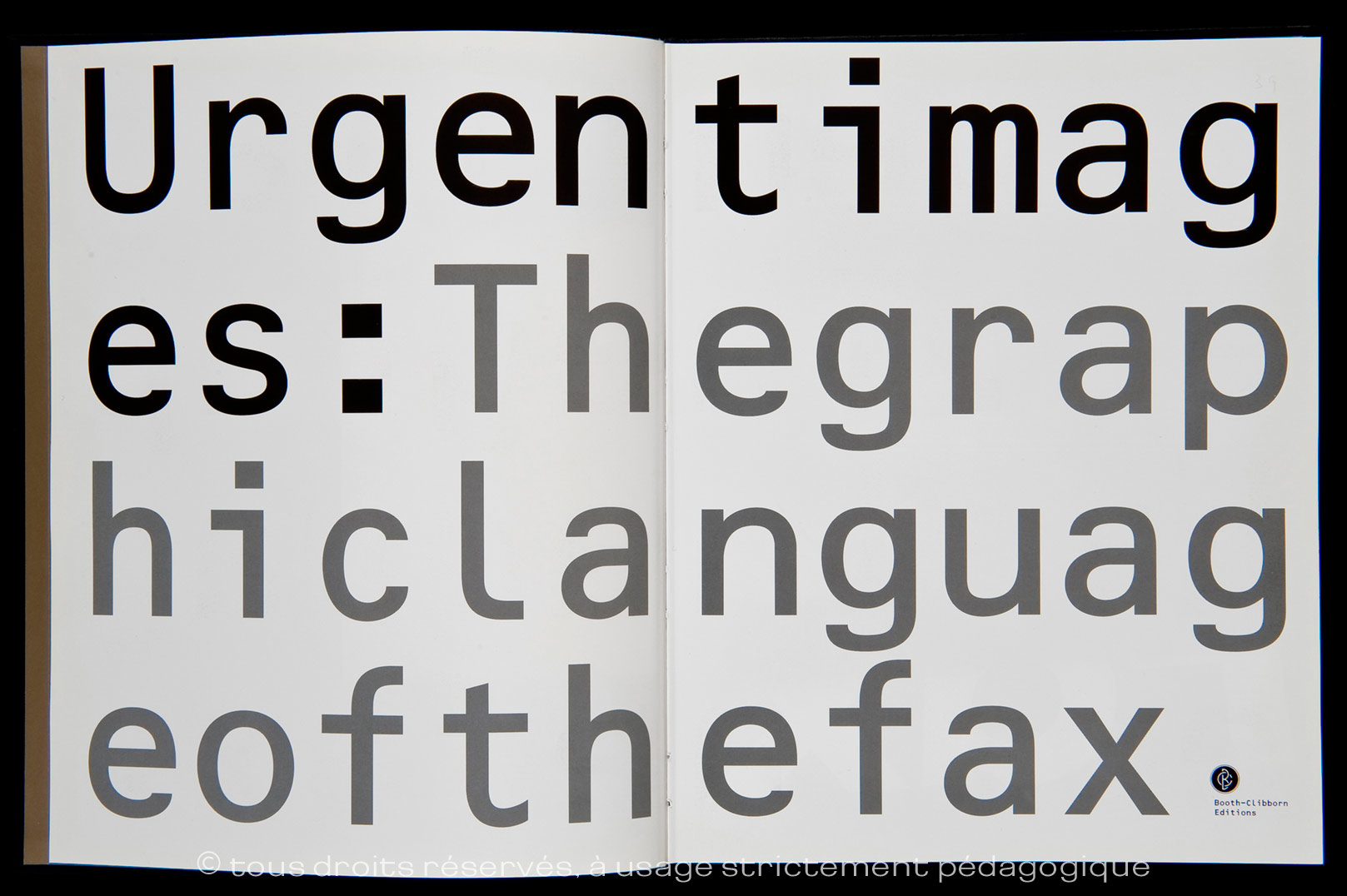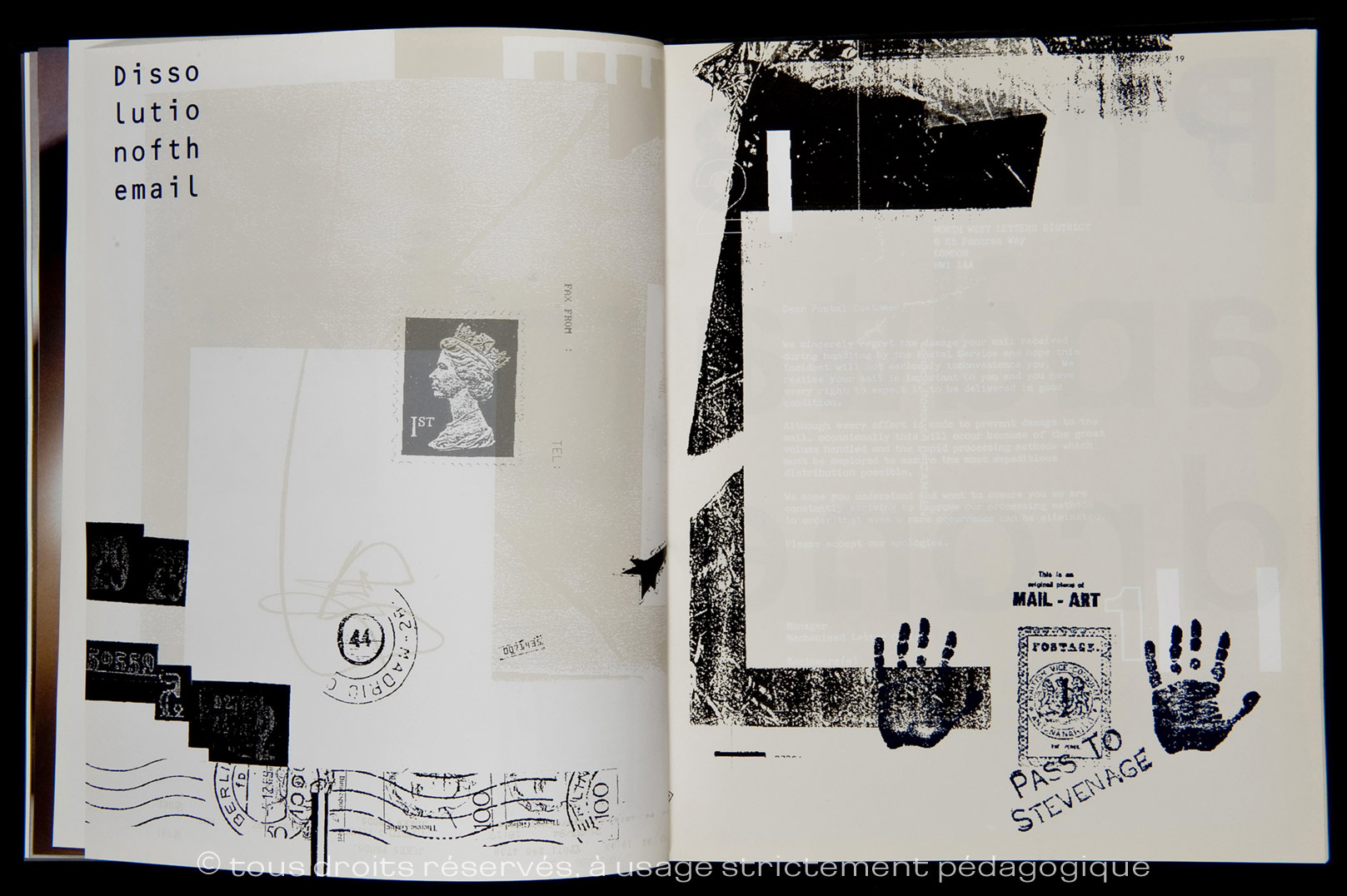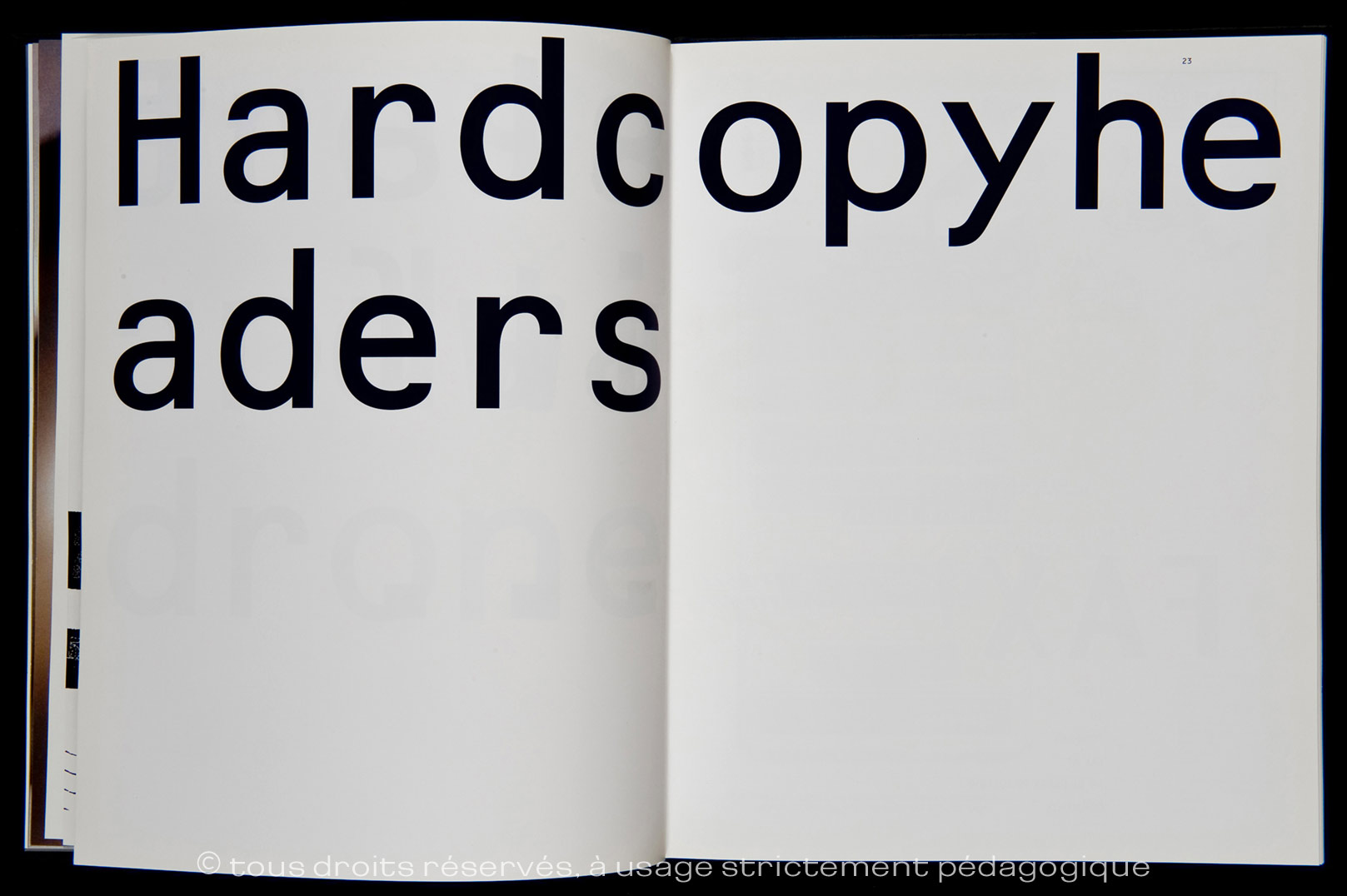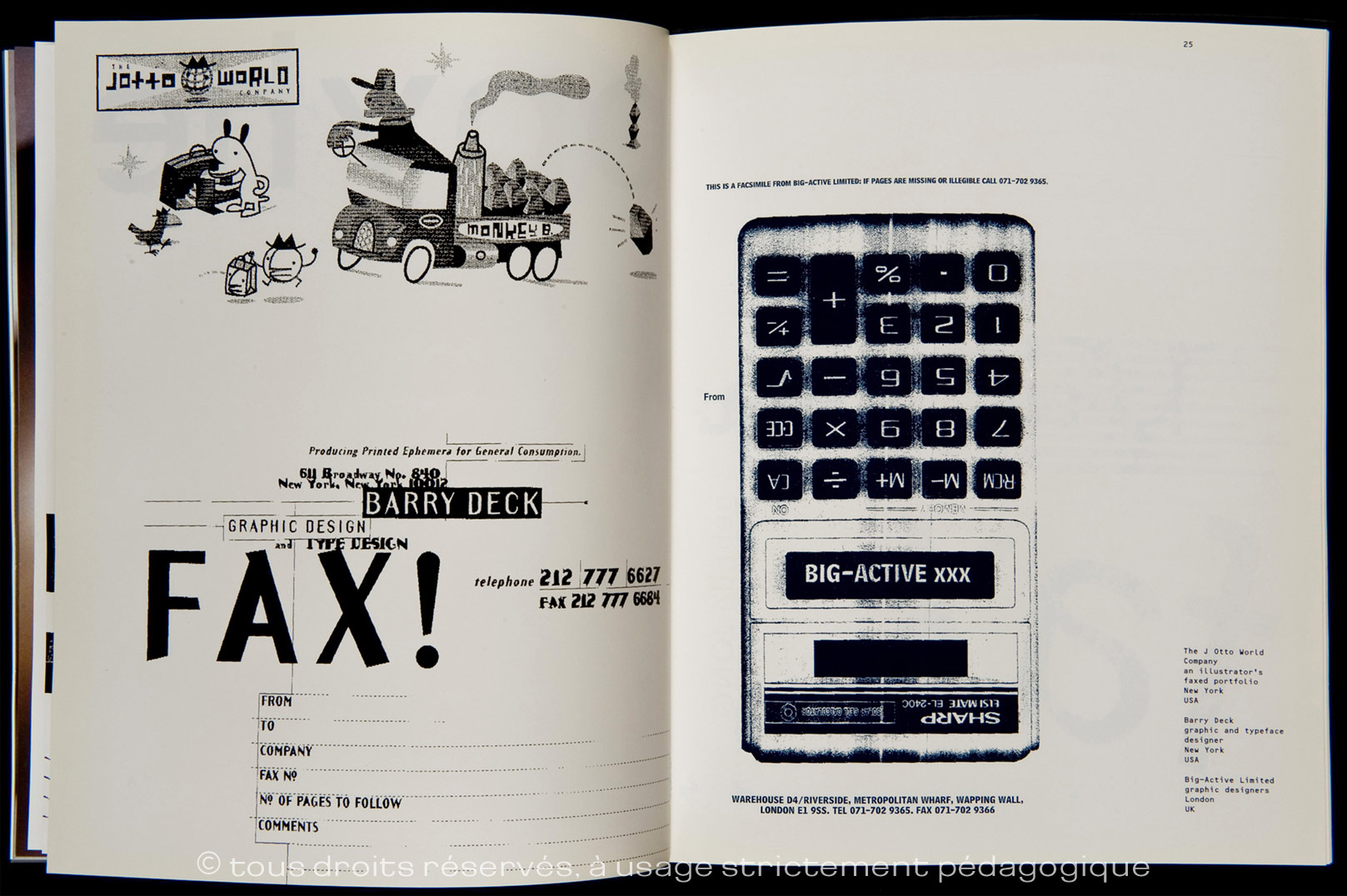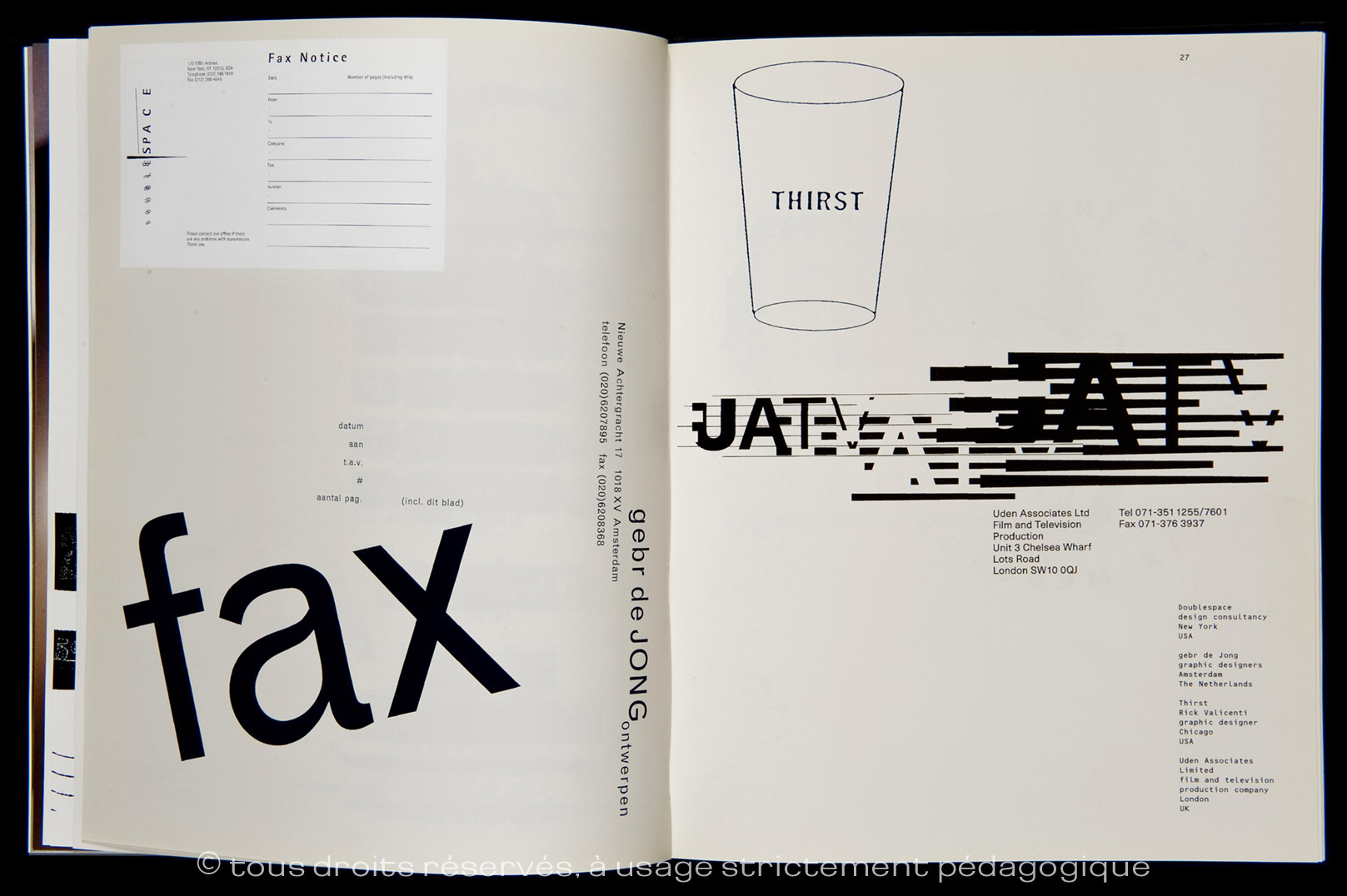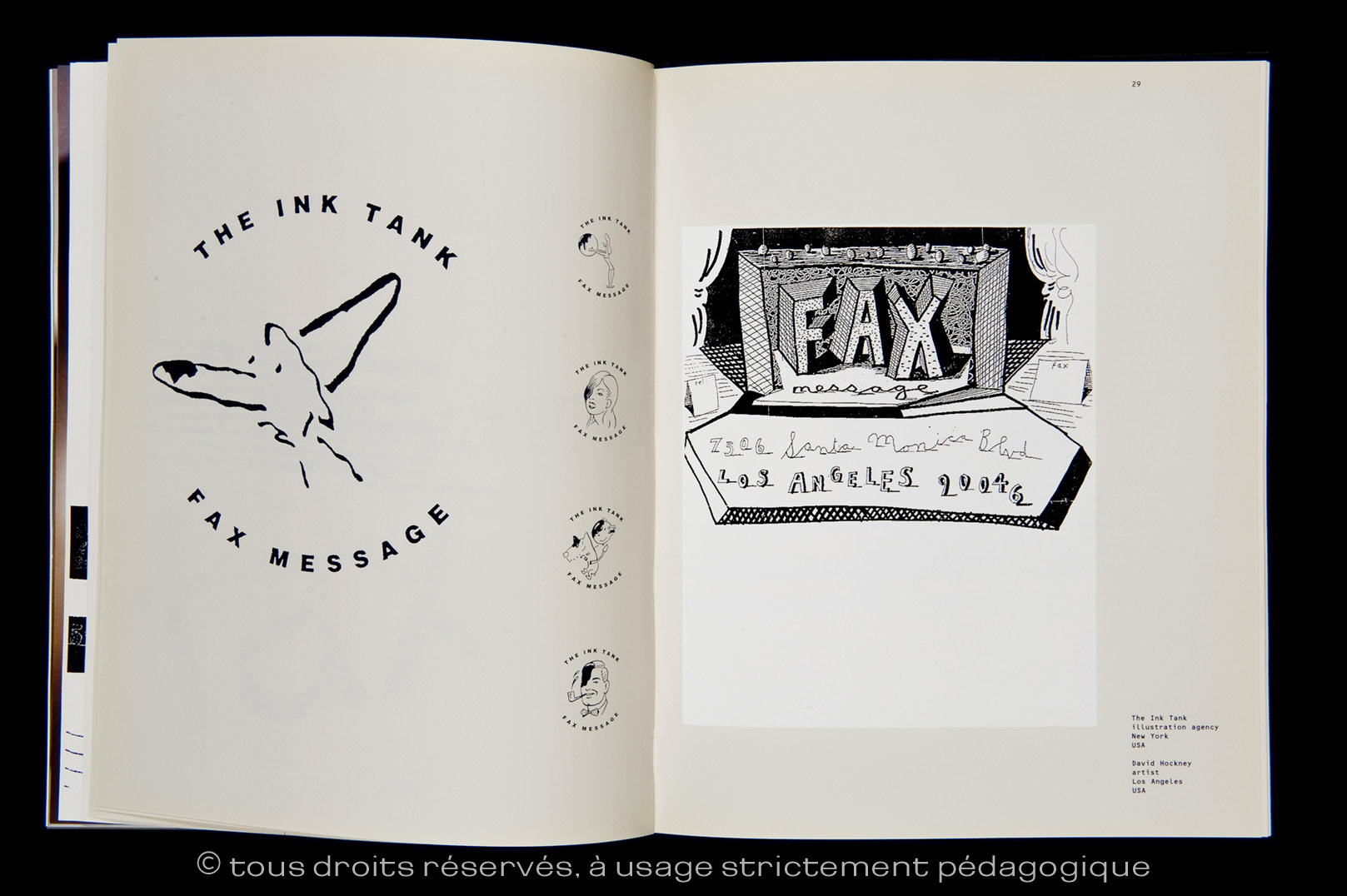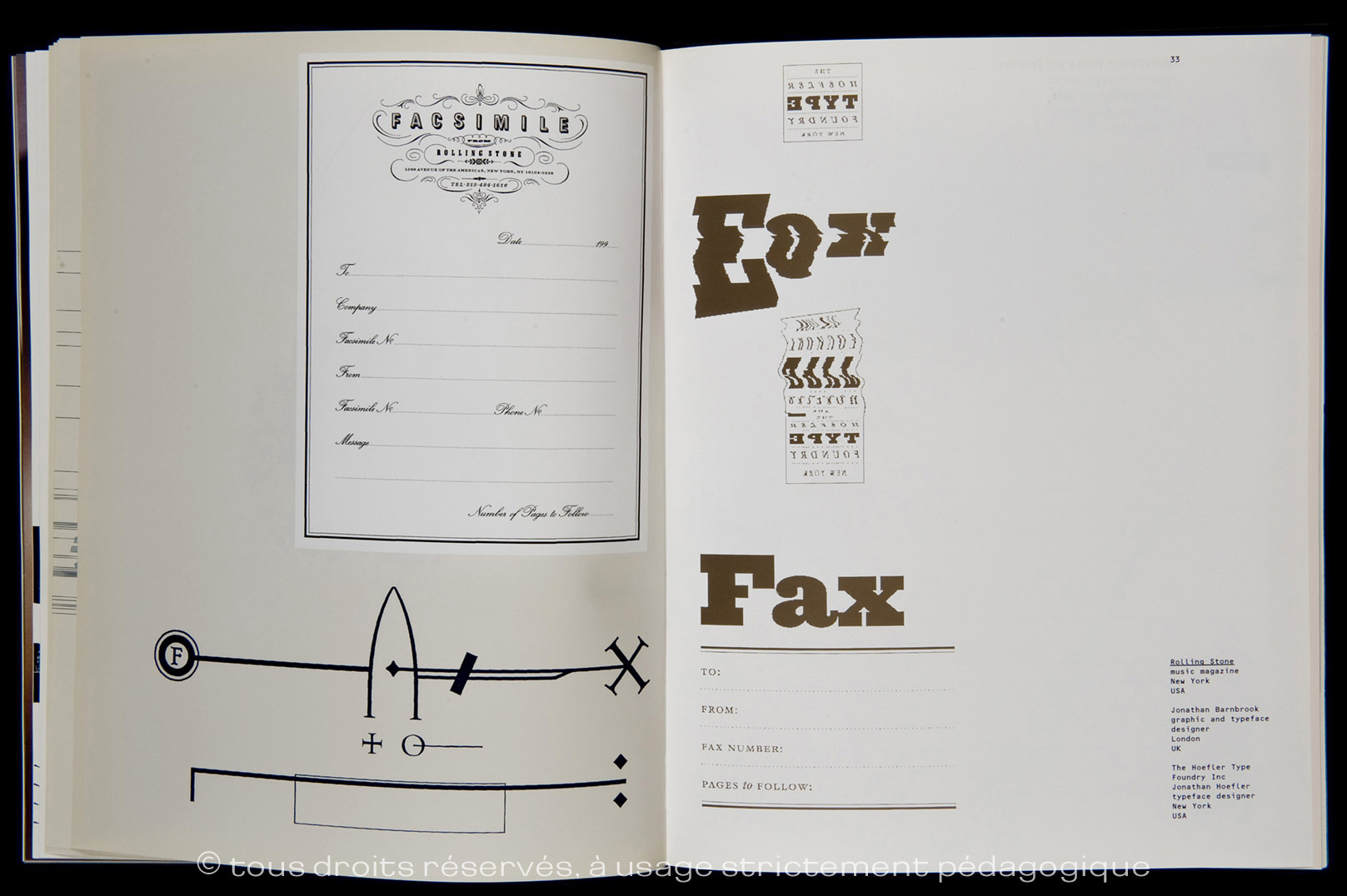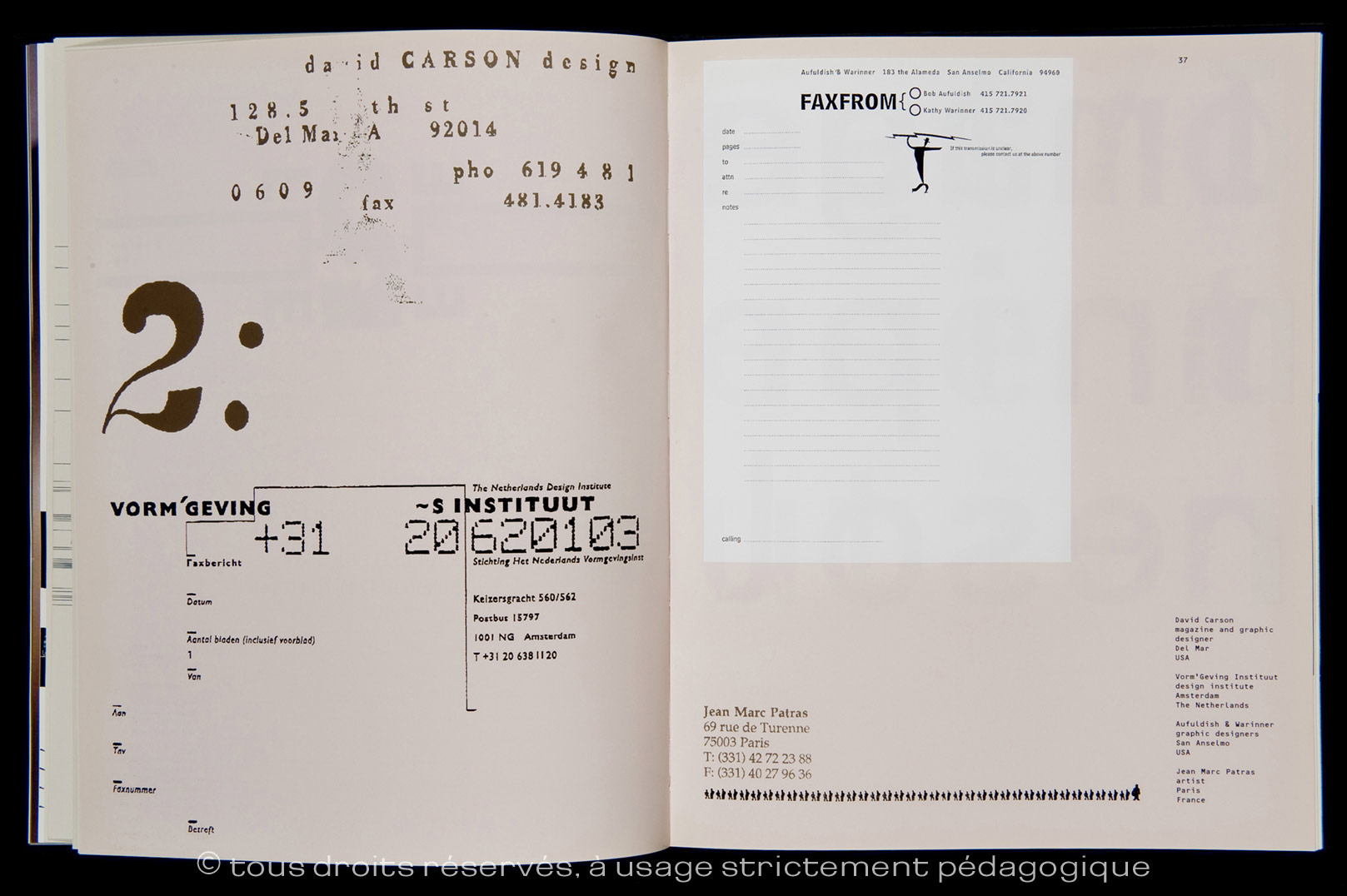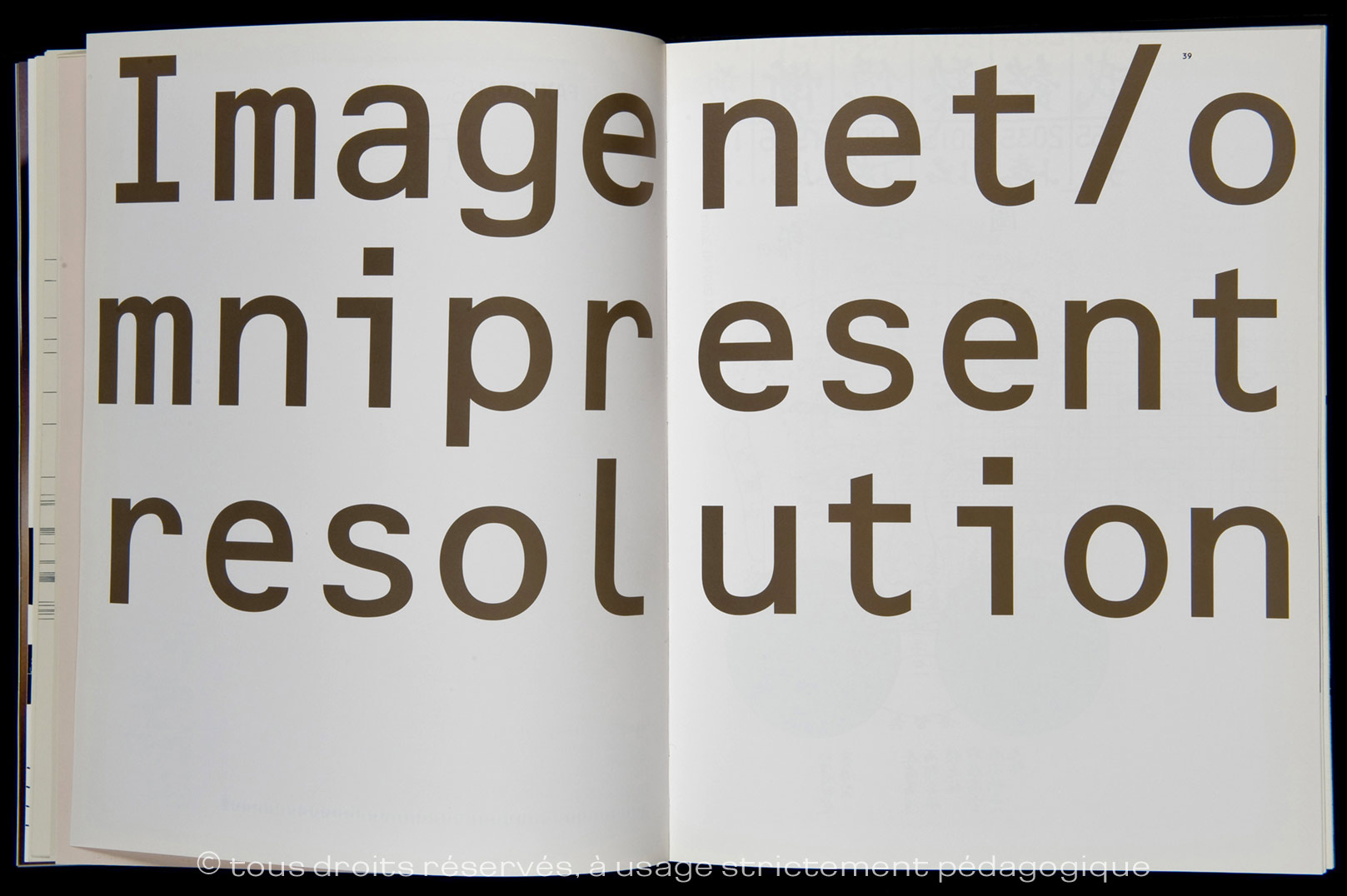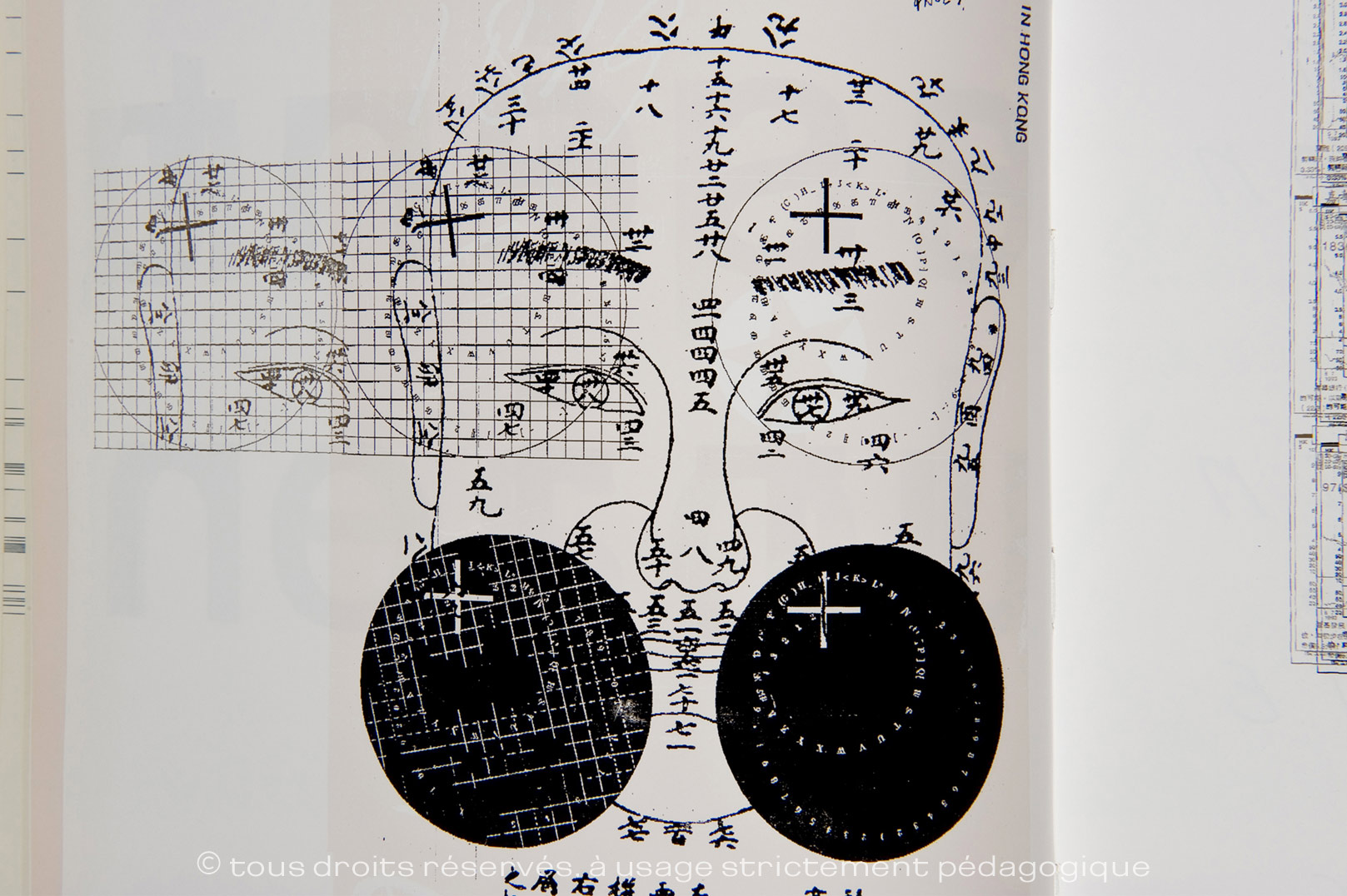
The Graphic Language of the Fax | de Edward Booth-Clibborn et Liz Farrelly
C’est sous le numéro ISBN 1873968 175 que l’éditeur Edward Booth-Cliborn a publié cet ouvrage en 1994, soit très exactement 5 ans après l’arrivée du numérique Mass Market avec les applications WYSIWYG d’Adobe (Adobe Type Manager) et les polices postscript de Type I. Pour resituer cette publication il faut savoir que nous étions juste après la première grande vague qui a balayé toute la typographie traditionnelle et qui allait dans les mois qui suivirent balayer également les métiers de la photogravure, de la photographie argentique et de la retouche photo. Un exemple, en 1993, sur un Macintosh FX, il fallait compter 20 minutes pour «ouvrir» une image pleine résolution 300dpi au format…A4. Aujourd’hui on compte par fraction de seconde.
La nécessité de ce livre de référence ne tient d’ailleurs pas aux inventions technologiques des ordinateurs mais bien plutôt à ponctuer la fin d’une époque où les graphistes, artistes graphiques, designers et auteurs s’exprimaient encore à l’aide d’outils électroniques comme la photocopieuse à laser ou les Fax chimiques ou transferts thermiques. Vous reconnaîtrez d’ailleurs les styles transgressifs dont parle savamment Rick Poynor et que j’ai évoqué de nombreuses fois sous l’appellation des styles DaDa. Car curieusement, c’est bien au DaDa qu’on a envie de songer lorsqu’on découvre le foisonnement des styles pré-numériques que propose The Graphic Language of Fax. (Vous tapez DaDa dans l’outil de recherche de Design et Typo et vous verrez ce que nous évoquons là.)
Design du livre: Angus Hyland et Silvia Gaspardo Moro
Voici le premier fax moderne à rouleau de papier photochimique qui envahit les agences de publicité et les bureaux de création dès 1974. Les responsables de la production transmettaient les copies dactylographiées à leur fournisseur de composition typographique tous les soirs, pour voir leur commandes réalisées dans la nuit et livrée au petit matin dans les services de production des agences.
L’histoire du Fax remonte au début du XXe siècle (voire la fin du XIXe) tel que vous pouvez le découvrir sur Wikipedia
Sur Wikipedia voici les dates que l’on trouve:
Le premier essai de fax est réalisé en 1842 par l’inventeur franco-suisse Puthomme. Il dépose la demande de brevet le 27 mai 1843 pour la transmission de documents écrits utilisant le réseau télégraphique, ceci avant l’invention du téléphone et du bélinographe d’Édouard Belin. Il utilise sa connaissance des pendules électriques pour produire des mouvements de balayage de va et vient ligne par ligne. Le premier fax ou Pantélégraphe est vendu en 1861 par Giovanni Caselli avant même l’invention d’un téléphone utilisable (4 800 dépêches entre Paris et Lyon en 1866).
Le docteur Arthur Korn, un Allemand, effectue le premier transfert de photographies par le téléphone en 1902.
Édouard Belin perfectionna ce procédé en 1907 avec son bélinographe.
1910: Korn réunit Berlin, Paris et Londres par « Fax ».
1922: Premier système pour un service de Fax par AT&T.
1927: NEC transmet les images du couronnement de l’empereur du Japon.
1931: Ouverture du premier service français de transmission de photographies par Bélinographe.
1936: NEC transmet les images des jeux de Berlin.
1942: La poste du Troisième Reich utilise le Fax pour les télégrammes.
1943: Première autorisation pour une utilisation privée de Fax.
1965: La firme allemande du Docteur HELL produit le premier Fax haute vitesse avec une transmission électrostatique.
1966: Rank Xerox développe le LDX1 qui pouvait transmettre une page A4 en 4 sec. au moyen de 32 lignes téléphoniques.
1970: Le premier fax « numérique » est proposé par Ricoh.
1971: Premier fax à technologie laser.
1972: Rank Xerox ouvre le marché du fax en Allemagne (TC400).
1976: Le CCITT publie les recommandations Groupe 1 et Groupe 2
1979: La Deutsche Bundespost ouvre un service Fax Groupe 3.
1980: Le CCITT publie les recommandations Groupe 3.
1986: Le CCITT publie les recommandations Groupe 4, classe 1.
1988: Allemagne 198 000 lignes fax. Monde 7,5 millions d’utilisateurs.
1989: En France, premières installations de Fax G4 sur NUMERIS.
1990: En France, plus de 350 000 fax en service.
1991: En France, plus de 200 000 fax vendus, apparition des premiers fax laser papier normal agréés.
1992: En France, 290 000 fax vendus, parc supérieur à 1 million. Plus de 25 millions de fax en service dans le monde. Développement du marché des fax papier normal (laser et jet d’encre), des PHONEFAX et des fax personnels.
1993: France: 323 000 Fax vendus, parc entre 1,2 et 1,5 million. Europe: Marché de 2 millions de fax, parc entre 7 et 8 millions. Monde: Plus de 32 millions de fax en service. Développement du marché des fax personnels multi-fonctions.
1995: PHONEFAX multi-fonction papier normal (transfert thermique) par SAGEM.
Cependant au travers de ce livre ce n’est pas tant une leçon de techno que je vous propose mais bien plutôt à un voyage sensoriel dans un foisonnement d’expressions typographiques et iconographiques qui anticipera tout au long des années 80 sur la grande explosion graphique du monde numérique tel qu’on le connait aujourd’hui. Ici point de grille, parce que les graphic designers qui transmettaient quotidiennement des messages faxés n’avaient ni le loisir ni l’envie de construire des pages cohérentes. Nous voyageons en pays de sensibilité, de texture et de contrastes à la place d’une architecture de pages traditionnelles.